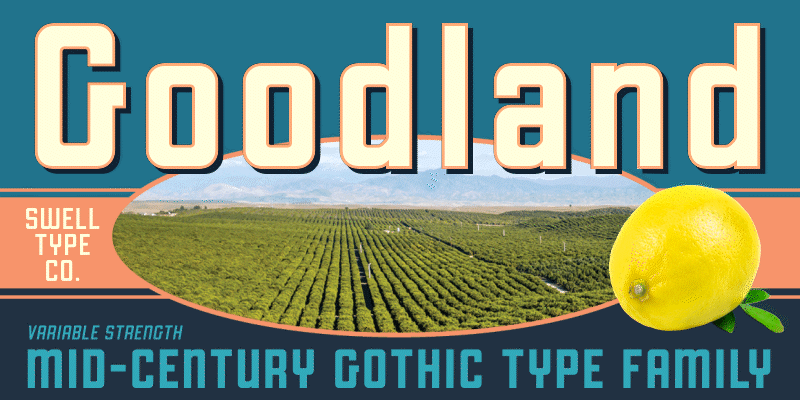
만화책, 비디오 게임, TV 프로그램 및 영화에 사용되는 글꼴 디자이너로서 수십 년간의 경험을 바탕으로 빌드된 John Roshell의 Swell Type은 캘리포니아의 실제 표지판과 풍경에서 영감을 얻었으며, 그래픽 디자인과 브랜딩 프로젝트를 위한 재미있고 친근하며 기능적인 글꼴입니다.